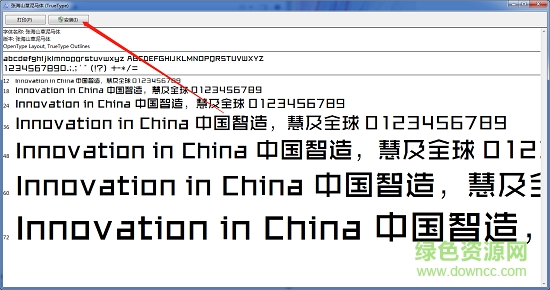
張海山草泥馬體是一款筆鋒剛硬的設(shè)計(jì)字體,字體角度分明,干凈整潔,非常適用于醒目標(biāo)題設(shè)計(jì)處,讓字體整體看起來(lái)非常的舒適,需要的用戶(hù)快來(lái)綠色資源網(wǎng)下載吧!
張海山草泥馬體是一款書(shū)寫(xiě)風(fēng)格設(shè)計(jì)方面的字體。字體剛勁有力,完美無(wú)比,可應(yīng)用于卡通設(shè)計(jì)、繪畫(huà)藝術(shù)、產(chǎn)品創(chuàng)意、平面廣告、印刷包裝等領(lǐng)域,喜歡的朋友可免費(fèi)下載收藏!